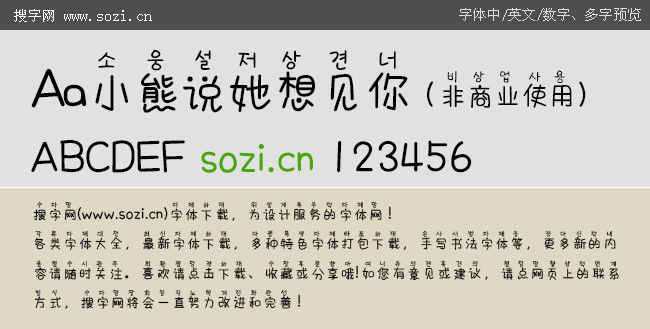
Aa小熊說她想見你
搜字網(wǎng)給大家提供一款A(yù)a小熊說她想見你(非商業(yè)使用)中文字體下載,該字體是一款個(gè)性的藝術(shù)字體,字體充滿變化,童趣十足。具有很好的視覺感,適用于平面宣傳設(shè)計(jì)、網(wǎng)頁設(shè)計(jì)、海報(bào)設(shè)計(jì)等應(yīng)用(此字體為個(gè)人非商用版,商用可以聯(lián)系QQ:1006760504)。